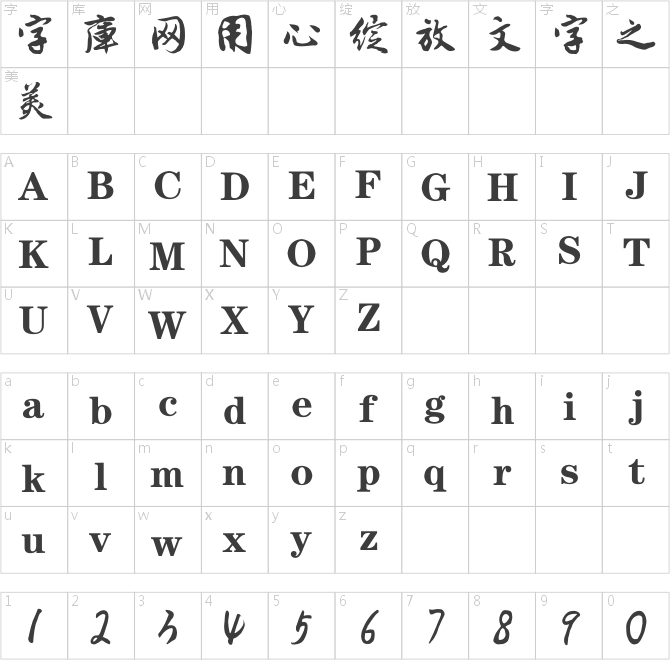
字体名称: 逐浪唐寅行书体
逐浪唐寅行书体
逐浪唐寅行书体介绍
明代才子唐寅,字伯虎,其诗书画俱佳,其中行书作品传世颇多。
为此,逐浪字库团队专门整理,构建一套以唐寅行书为主体的书法字库。
标准样本:唐伯虎行书字帖《落花诗册》。
1、横线从左往右边提
2、字体在原帖基础上,注意丝连呼应,如“室”字。
3、按中华人民共和国简体字法规为规范,当一个字遇到原帖为繁体时,则简体相应部份也用繁体,避免生造字与原帖精神不符。
根据国家GB2312-80标准,涵括了常用的6763个字。
而逐浪出品,则包括现代常用字符、拉丁补充字符、生僻字符集,总库达九千多个字符,匠心之作,方便设计、排版、出版、网店、印刷等各界行业使用。
逐浪唐寅行书体效果图